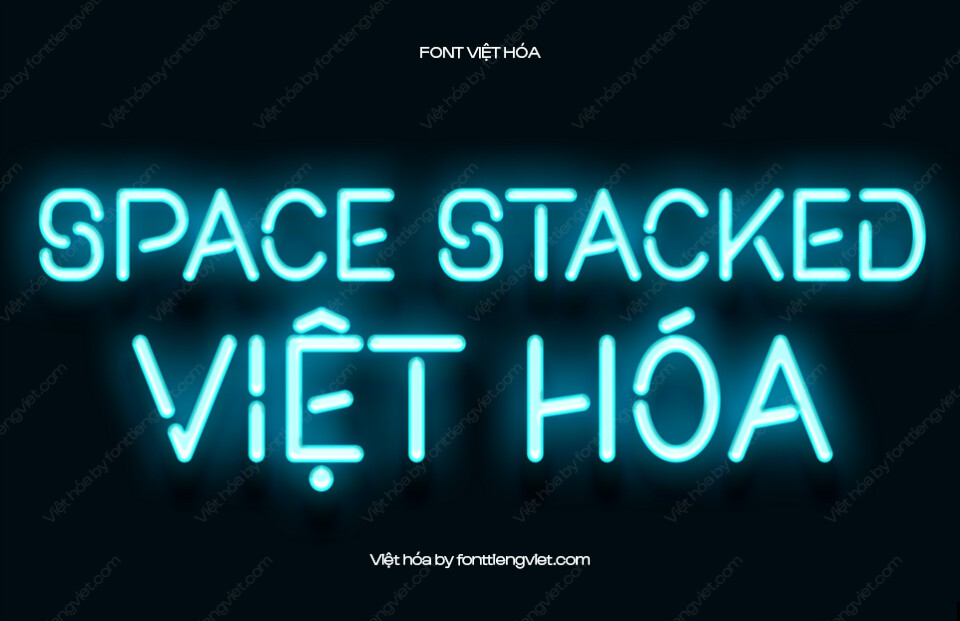
Trong thế giới thiết kế đồ họa hiện đại, việc tìm kiếm một bộ Font Chữ độc đáo và ấn tượng luôn là ưu tiên hàng đầu của các bạn học sinh và giáo viên. Font Việt hóa 1FTV VIP Space Stacked – Kiểu Neon xuất hiện như một làn gió mới, mang đến vẻ đẹp mang đậm hơi thở tương lai. Đây là font chữ được tối ưu hóa hoàn toàn cho tiếng Việt, giúp người dùng dễ dàng tạo ra những ấn phẩm truyền thông hoặc bài thuyết trình sinh động mà không lo lỗi hiển thị ký tự đặc biệt.
Đặc điểm nổi bật của Font Việt hóa 1FTV VIP Space Stacked – Kiểu Neon
Bộ phông này gây ấn tượng mạnh mẽ nhờ cấu trúc chữ xếp chồng đặc biệt, mô phỏng chân thực hiệu ứng đèn Neon rực rỡ trong không gian. Khi sử dụng Font Việt hóa 1FTV VIP Space Stacked – Kiểu Neon, các thiết kế của bạn sẽ trở nên nổi bật với chiều sâu 3D đầy lôi cuốn. Kiểu chữ này cực kỳ phù hợp cho các tiêu đề lớn, banner sự kiện trường học hoặc bìa giáo án điện tử cần sự phá cách.
Ứng dụng thực tiễn trong giáo dục và sáng tạo
Với phong cách hiện đại, Font Việt hóa 1FTV VIP Space Stacked – Kiểu Neon không chỉ dành cho dân chuyên nghiệp mà còn rất gần gũi với học sinh. Các em có thể dùng font này để thiết kế poster cổ động, làm báo tường số hoặc trang trí video clip ngắn. Sự kết hợp giữa đường nét khỏe khoắn và hiệu ứng ánh sáng giúp nội dung truyền tải trở nên hiện đại, bắt kịp xu hướng tối giản nhưng tinh tế.
Để phát huy tối đa vẻ đẹp của bộ chữ, người dùng nên kết hợp với các tông màu tối hoặc nền đen để hiệu ứng Neon tỏa sáng rõ rệt nhất. Font đã được Việt hóa kỹ lưỡng, đảm bảo độ tương thích cao trên nhiều phần mềm thiết kế phổ biến. Đây chắc chắn là công cụ không thể thiếu trong kho tài nguyên của những ai yêu thích sự sáng tạo mới mẻ.